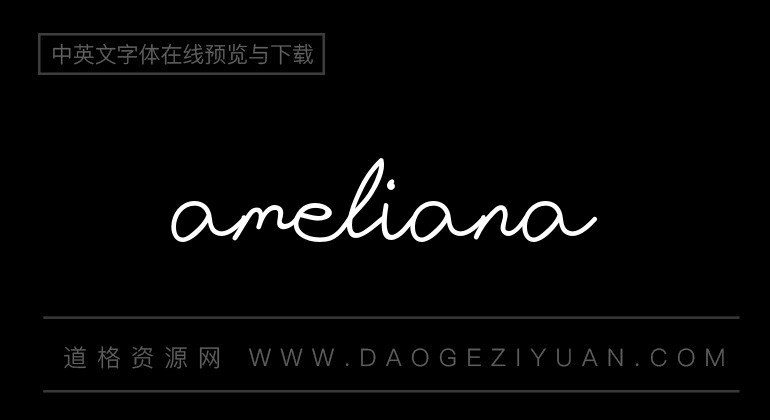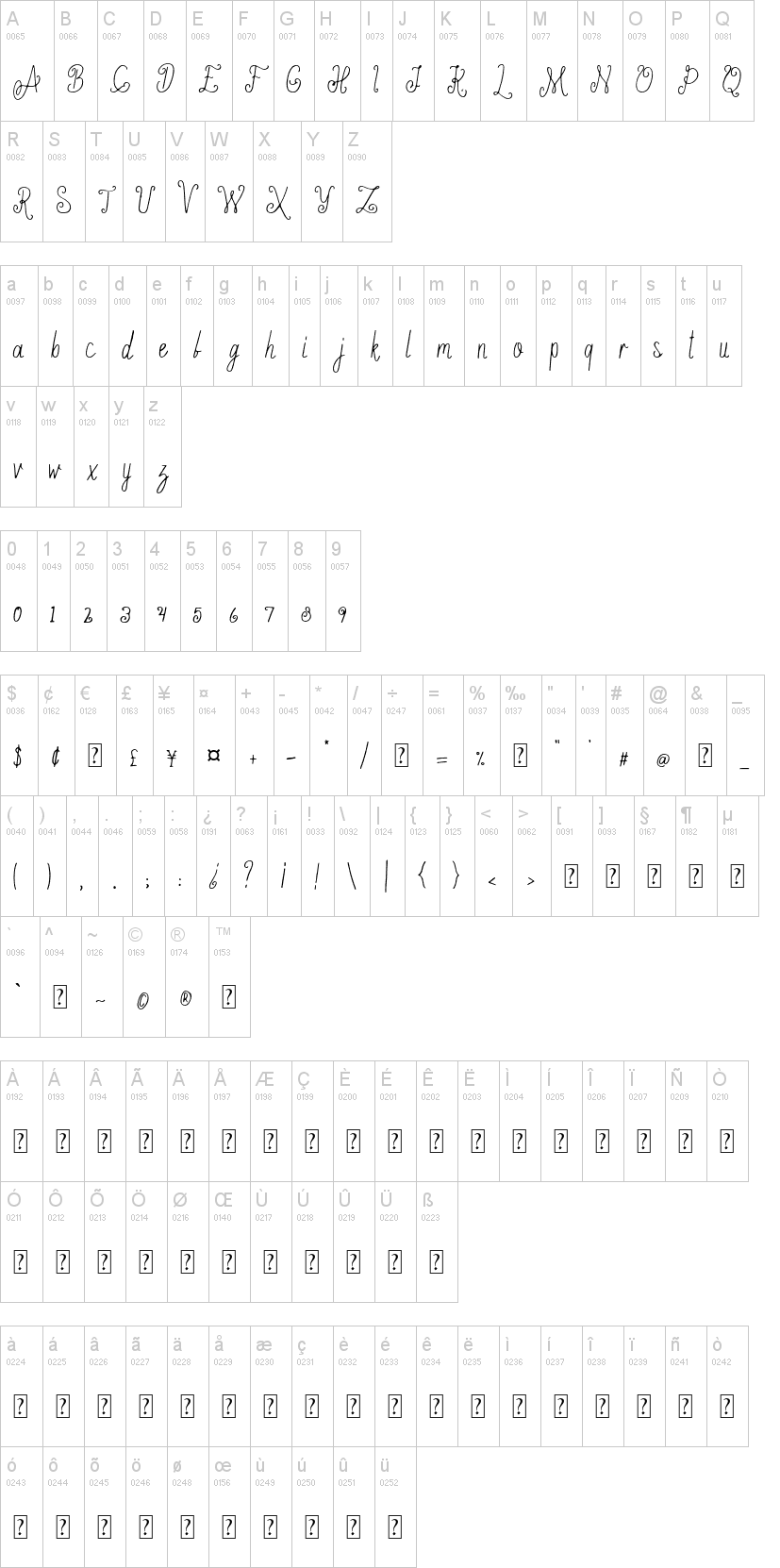
Ameliana
? Ameliana是一款现代视觉字体,它的特点是极具灵活性,可以根据不同的需求进行调整,以满足设计师的要求。它的字体结构特别精细,拥有柔和的笔画和清晰的轮廓,使得它特别适合创作精致的文字图案。它的细节非常丰富,可以提供更多的表现形式,从而使得文字看起来更加精美。同时,它的字符间距也很宽,使得文字显得更加整洁,更加精致。
Ameliana是一款非常不错的手写艺术字体,具有很好的视觉感,适合于文化类的宣传设计、商业类品牌的广告和产品包装设计以及个性化文字排版等较多场景。
Ameliana字符映射图